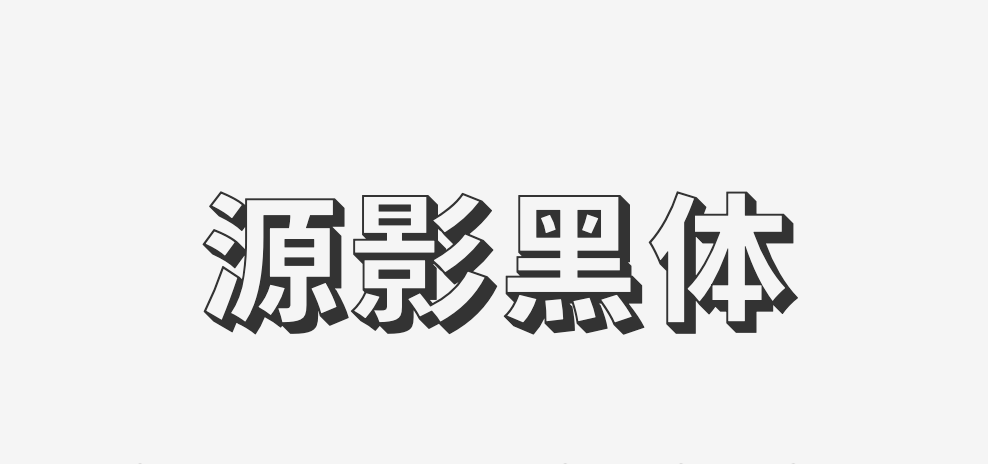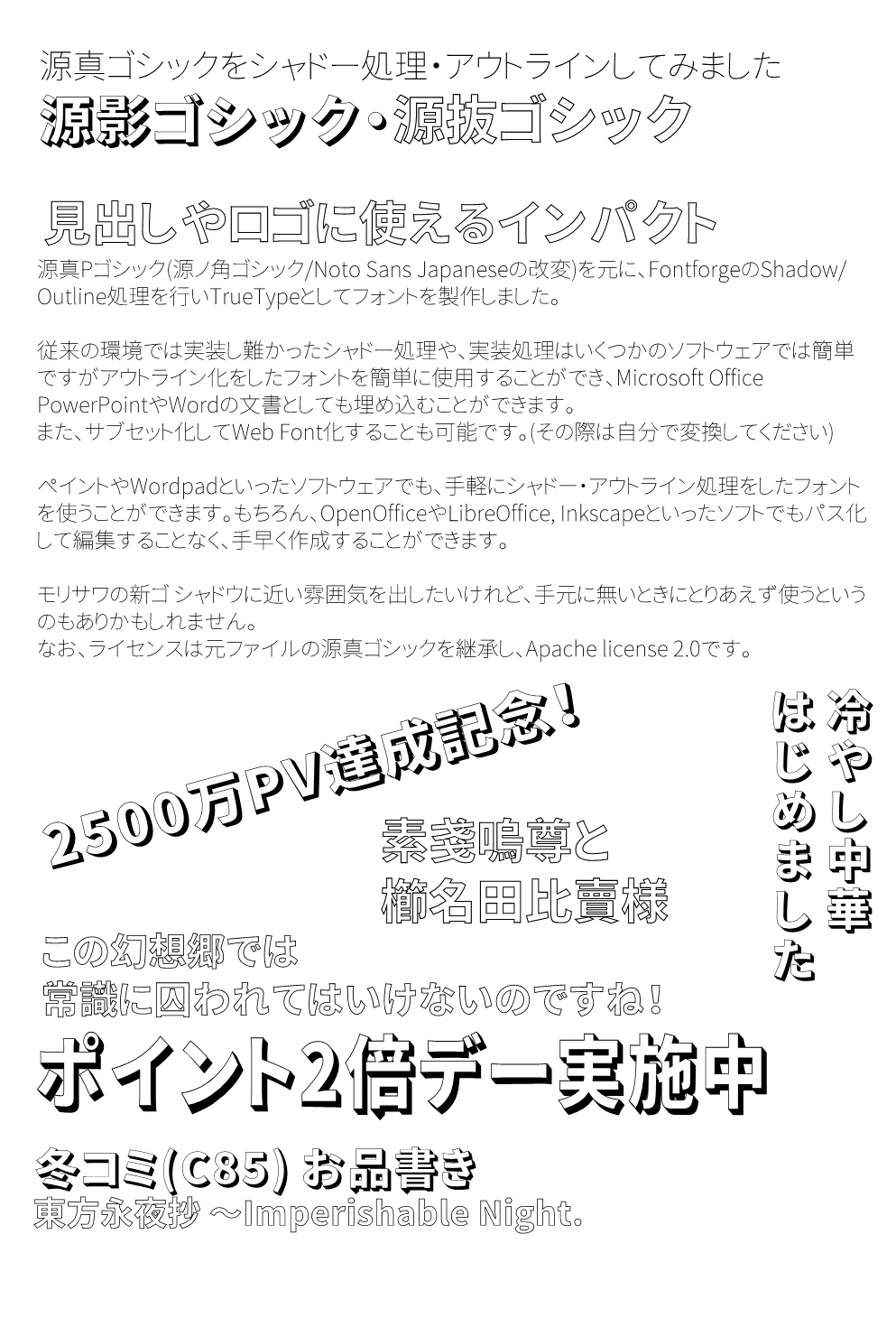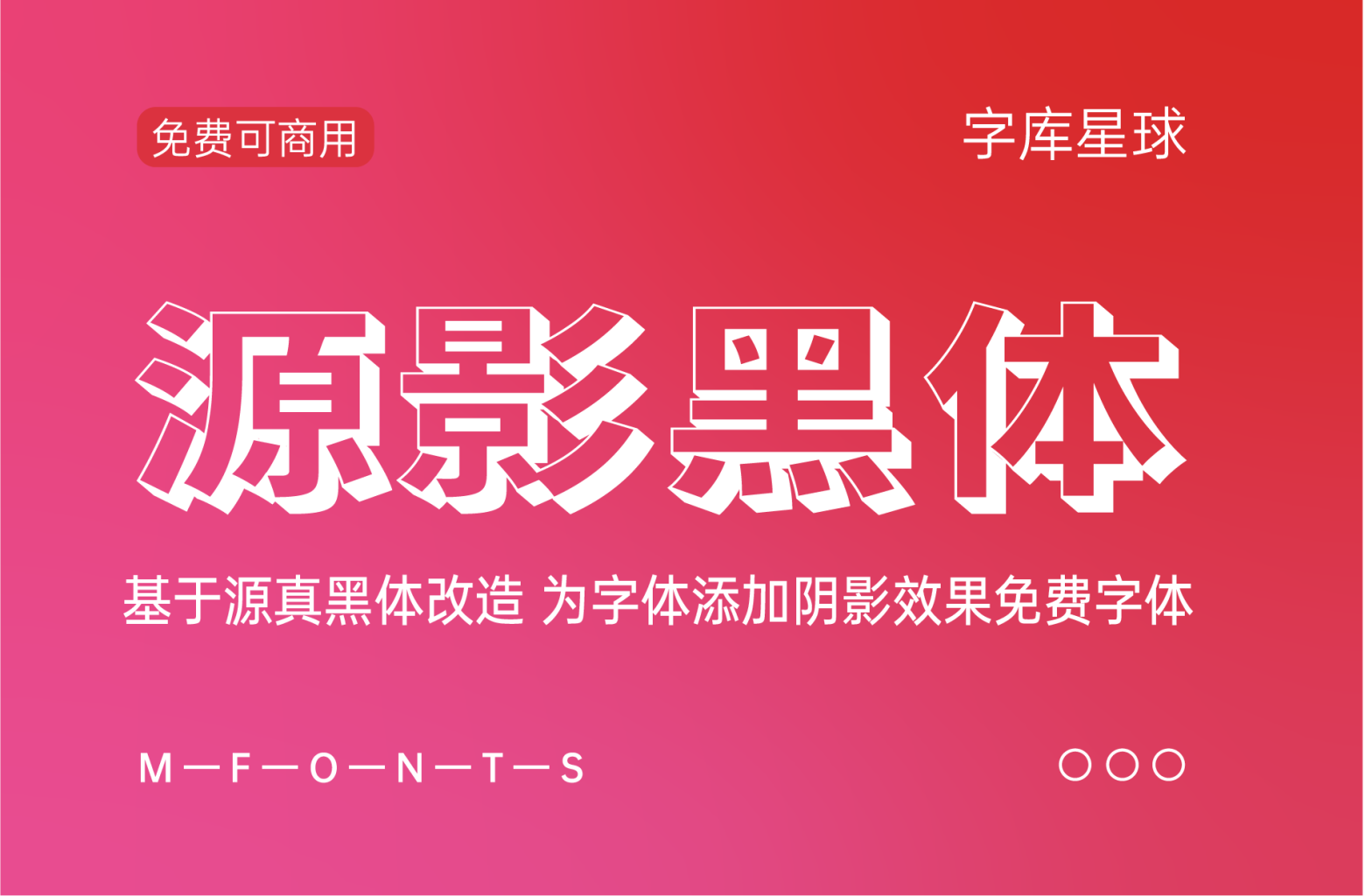
源影黑体(日文名:源影ゴシック)是基于Genshin Gothic P Heavy版本通过Fontforge软件添加的轮廓处理和阴影处理而成的字体。
制作这款字体的初衷是,在某些场景下,你很难通软件去制作字体的阴影效果,这款字体就能很好地解决阴影难添加的问题。
这个概念可能类似于森泽的“Shin Go Shadow”或 Type Lab 的“Anito Inline”。
之前日本著名字体设计公司Fontworks也发布过一款类似的字体壁垒Rampart,大家如果有兴趣的话可以看一下。这两款字体不同之处在于壁垒Rampart具有倾斜角度,而且字体更偏高瘦。而源影黑体则是普通的思源黑体添加了阴影效果。
文章标题:源影黑体